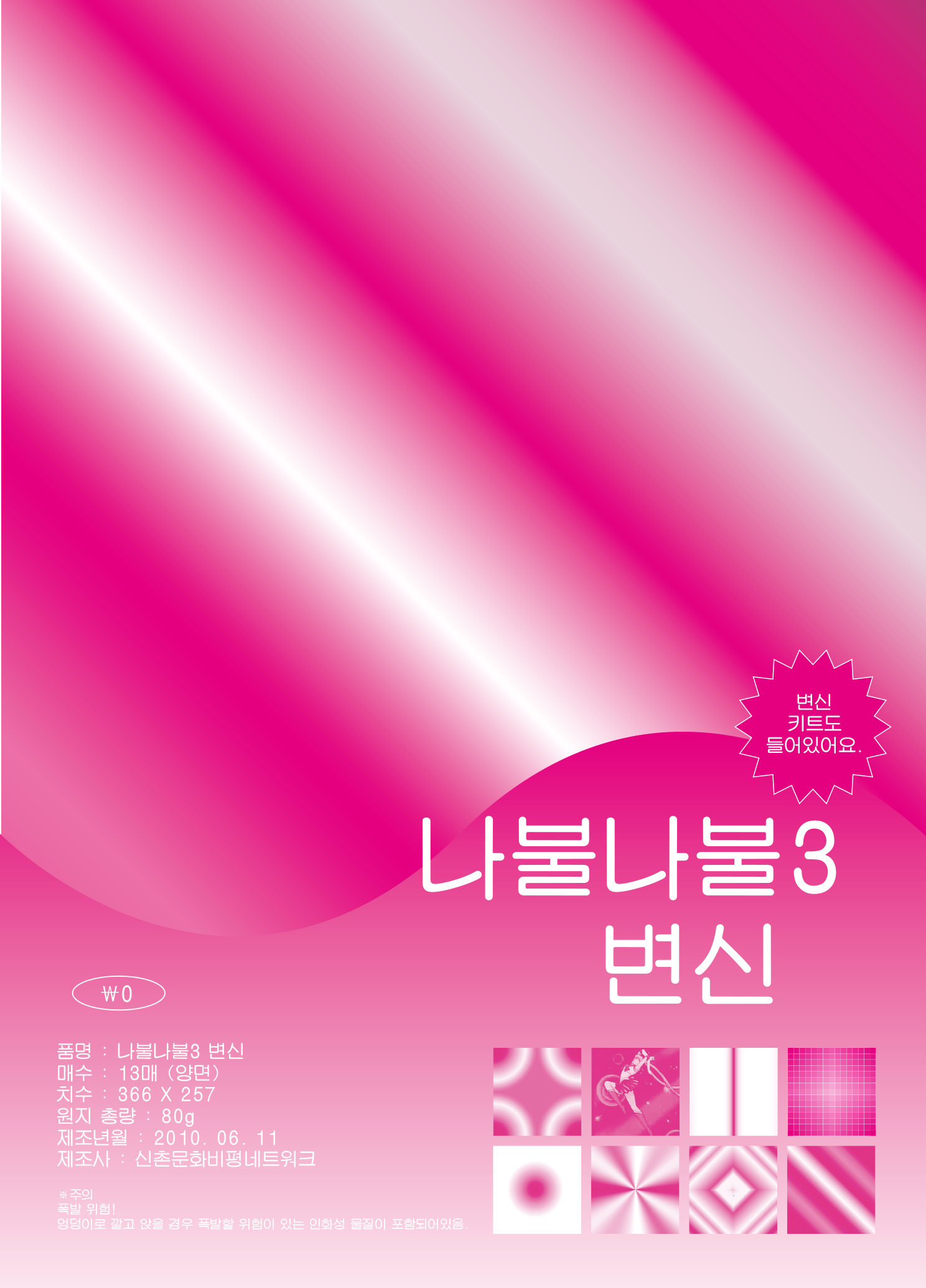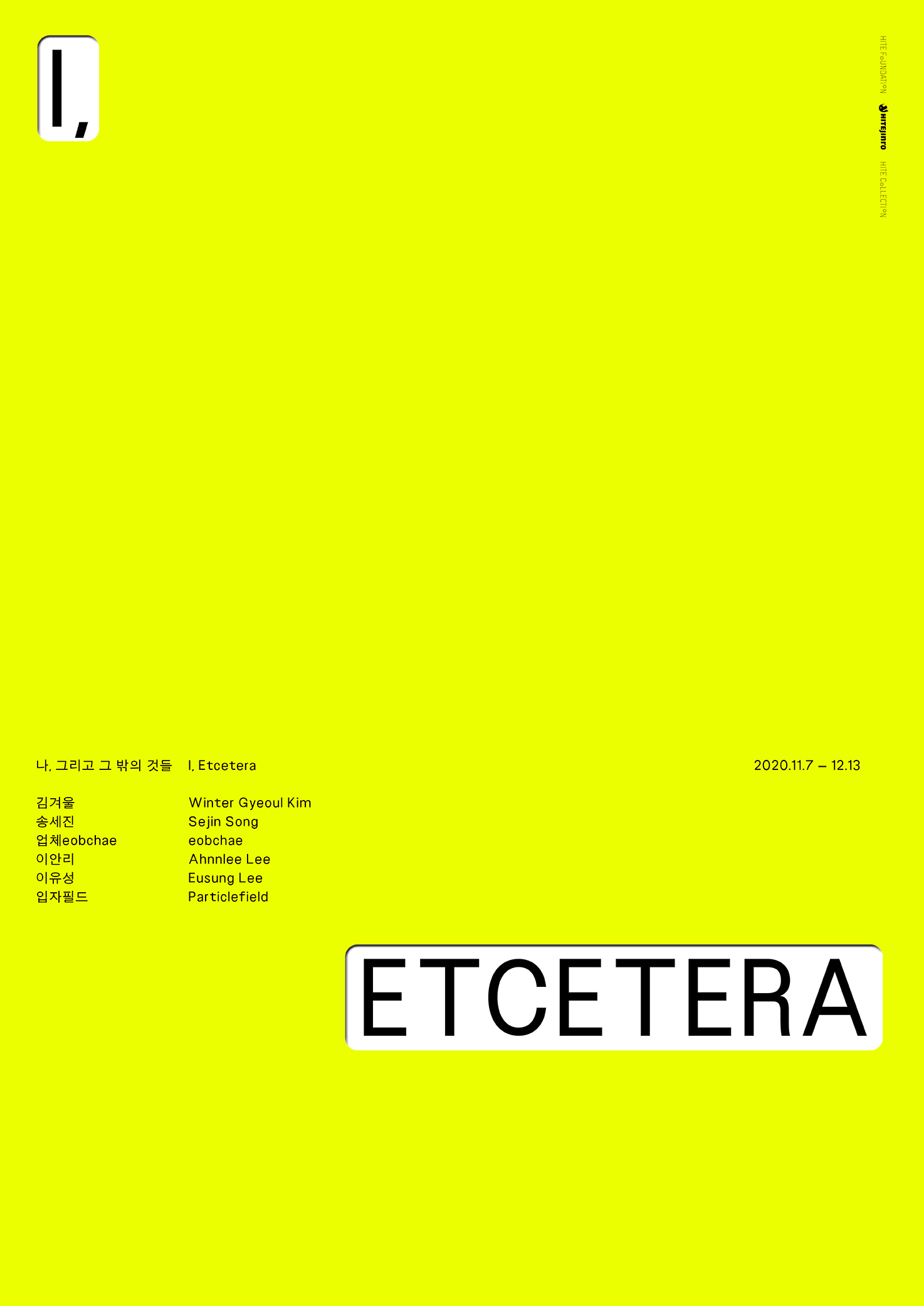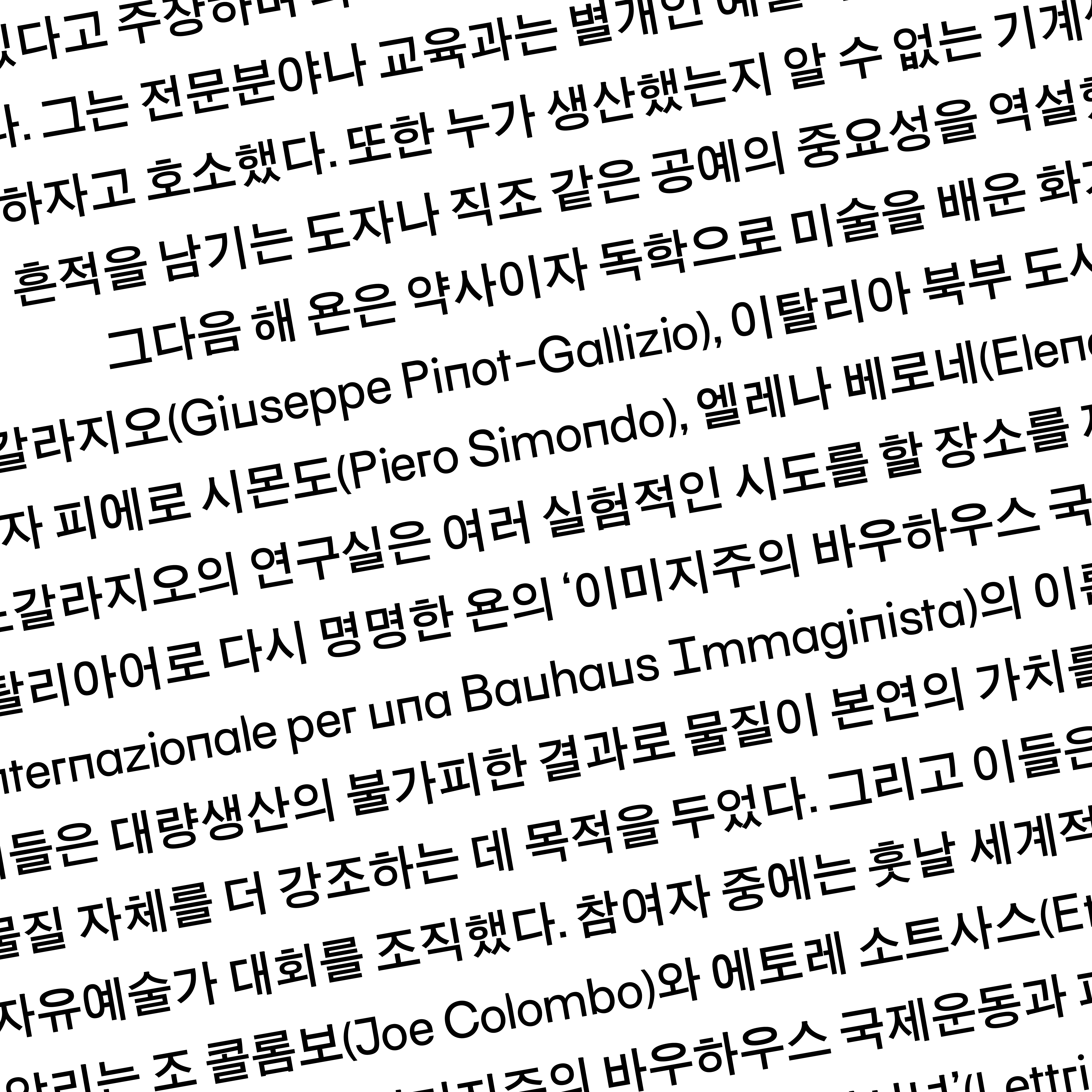
일상에서 우연히 만나는 이미지들은 디자이너의 디자인보다 더 멋있어 보일 때가 많다.
저자는 알 수 없지만 오랜 세월에 걸쳐 변형되온 이 시원(COOL)해 보이는 아이스박스 패턴도 마찬가지다.
그래픽 디자이너로서 주어진 내용에 알맞은 혹은 보기 좋고 ‘멋있는’ 이미지를 만들기 위해 고민하다 보면,
과연 “멋있는(COOL)’ 것은 무엇인가?”에 대한 질문을 항상 가지게 된다.
‘멋있는’ 것은 매우 주관적인 개념이고 각자가 생각하는 멋있음은 다르다.
그렇지만 어찌 되었든 절대적으로 ‘멋있는’ 것은 없다는 점,
고정된 이미지도 맥락에 따라 다르게 읽힌다는 사실은 그사이 지점에서
새롭고 재미있는 것을 만들어낼 수 있다는 힌트처럼 느껴져 작업의 원동력이 되기도 한다.
Q. SM폰트를 사용해 만든 작업 중 가장 기억에 남는 작업은?
SM나루체를 제목 서체로 사용한 잡지 나불나불 3호 ‘변신’. “‘변신’이라는 개념을 종이/책에 적용하면 어떤 디자인을 할 수 있을까?”라는 생각으로 출발해 ‘종이접기’를 떠올렸고, 학종이 패턴을 모티브로 한 디자인을 책 전체에 적용했다. 책의 표지는 학종이 패키지와 비슷하게 연출하고 싶었고, 당시 생각하기에 학종이 패키지에 사용된 것과 닮은 분위기의 서체를 찾다 sm 나루체를 사용했다. 잡지의 제호와 해당호 디자인 컨셉에 잘 맞는 서체를 사용한 예이기도 하고, 학부를 졸업할 즈음 디자인에 재미를 느끼게 되었던 작업이라 그런지 가장 기억에 남는다.
Q. SM폰트와 라틴 알파벳폰트와의 페어링 중 가장 좋아하는 조합은?
태고딕과 라틴 알파벳 Surt 서체 조합. 2019년에 디자인했던 국립현대미술관의 <<대안적 언어 - 아스거 욘, 사회활동가로서의 예술가>> 전시 도록에 사용한 조합이다. 작가의 특성과 서체의 인상을 맞추는 중에 한글 서체를 먼저 태고딕으로 정했고, 후에 태고딕과 밸런스가 잘 맞는 라틴 알파벳 서체를 조합해보던 중에 Surt를 찾게 되었다. Surt의 라틴 알파벳폰트의 옵션 중 각진 형태가 태고딕과 어울리면서도, 기존의 질서와 틀을 깨는 작가의 정신과 어울리기도 해 최종적으로 이 조합을 사용하였다. 별다른 설명 없이도 개성 있는 인상을 주어 SM폰트와 라틴 알파벳폰트와의 페어링 중 가장 좋아하는 조합이다.
Q. 내가 생각하는 SM폰트를 인상적으로 사용하는 디자이너가 있다면?
SM폰트 하면 워크룸 디자인이 생각난다. 아무래도 그래픽 디자인에 관심을 가지기 시작했던 시절에 워크룸의 SM폰트를 활용한 타입 중심의 모던한 디자인 - 서체의 인상이 디자인의 전체적인 분위기에 영향을 주는 - 을 많이 봐서 그런 것 같다. SM폰트하면 견출명조, 견출고딕, 신신명조, 중고딕 이렇게 4종이 가장 대표적으로 생각이 나는데, 이 4종의 인상적인 활용 예시들을 워크룸의 디자인에서 다양하게 봤던 것 같다. 포스터나 책 표지의 견출고딕, 이경수 디자이너의 섬세한 중고딕 그리고 김형진 디자이너가 사용한 <제안들> 표지의 견출명조 등이 SM폰트의 아이코닉한 사용 예시 같다.
Q. SM클래식 시리즈를 다른 사물에 비유한다면?
흰색이나 검정색 기본 티셔츠 같은 것 아닐까? 베이직해서 없어서는 안되는 아이템! 화려한 아이템에게 정신이 팔려 소중함을 잠시 잊기도 하지만 입지 않더라도 꼭 옷장에 있어야 하는 그런 것.
Q. 코로나 시대, 당신은 어떤 것에서 어떻게 영감을 받고 있습니까?
이전에는 몸을 움직이면서 새로운 곳에 가고 보고 경험하고 사면서 주로 외부적인 것으로부터 디자인을 위한 ‘영감’을 얻었다면, 환경이 바뀌면서 나와 나의 가까운 주변을 정돈하고 가꾸는 생활인의 면모가 중요하다는 것을 알게 되었다. 가족들, 친구들, 작업실 친구들, FDSC 디자이너들, 나와 소통하는 클라이언트분들 그리고 직접적으로 연결되어 있지 않더라도 나와 동시대를 사는 다양한 사람들의 삶의 방식과 태도에서 동기부여와 자양분을 얻는다. 특히 그래픽 디자이너라는 직업인이자 1인 사업자로서는 그래픽 디자이너 커뮤니티 FDSC(페미니스트 디자이너 소셜클럽)에서 만나는 다양한 디자이너들과 커뮤니티 활동을 통해 배우는 점이 많다.
[SM3태고딕]
<대안적 언어 – 아스거 욘, 사회운동가로서의 예술가> 도록 ∙ 2019
[SM3중고딕]
<나, 그리고 그 밖의 것들> 포스터 ∙ 2020
[SM3 디나루, SM3견출고딕]
<나불나불3: 변신> 잡지 디자인 ∙ 2010
양민영은 서울에서 활동하는 그래픽 디자이너. 디자인은 '불도저'라는 이름으로, 출판은 '불도저프레스'라는 이름으로 선보이고 있다.
잡지와 옷을 좋아하며 한국의 동시대 문화에 관심이 많다. 이를 바탕으로 옷과 스타일에 관한 잡지 <쿨>,
옷장 속 안 입는 옷을 정리하는 <옷정리>와 같이 옷에 관한 프로젝트를 진행하고 있다.